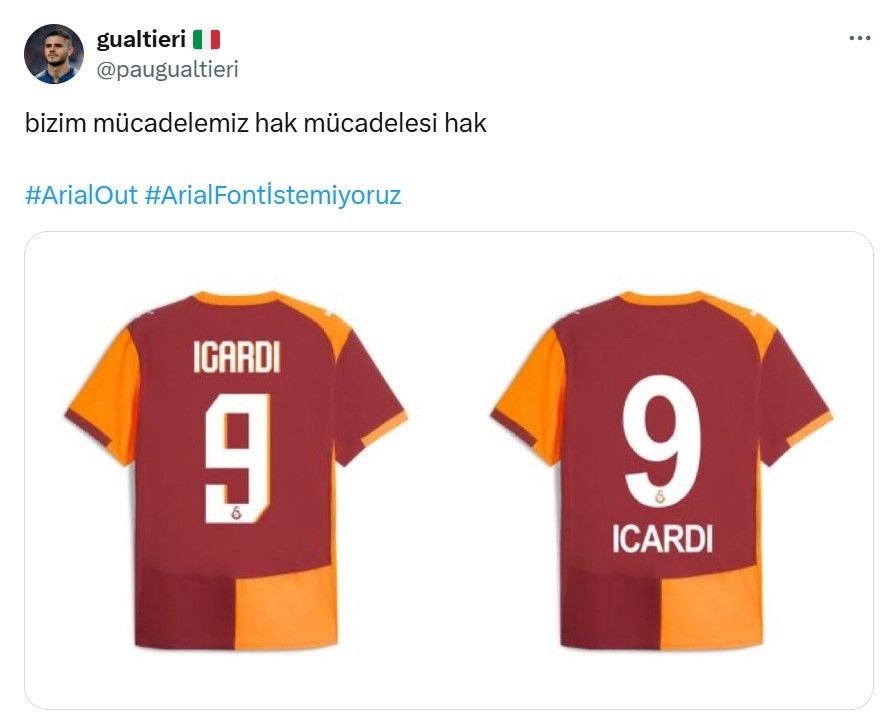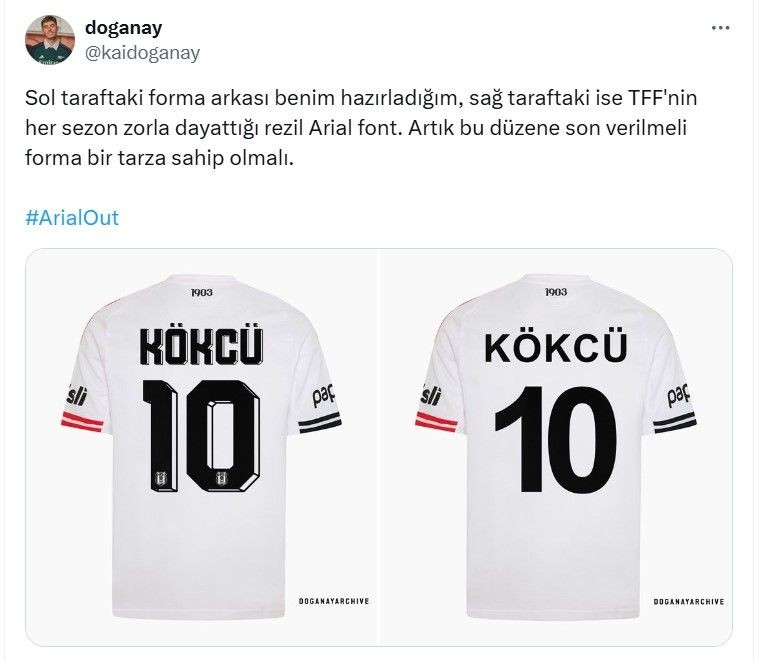
TFF'den 12 yıl sonra tarihi karar! Kural değişiyor
Türkiye Futbol Federasyonu, yaz boyunca taraftarların çağrılarına kulak verdi ve tarihi bir adım atacak.
Galatasaray, Fenerbahçe, Beşiktaş ve Trabzonspor taraftarları başta olmak üzere "#ArialOut #ArialFontİstemiyoruz" etiketleriyle TFF'ye çağrıda bulunmuştu.
Futbolseverler, formalarda Arial font kullanımının zorunlu olmasına tepki göstermiş ve bu konuda çok sayıda paylaşım yapılmıştı.
Umut Eken’in haberine göre TFF Genel Sekreteri Abdullah Ayaz, özellikle sosyal medyadan gelen tepkiler sonrası konuyu gündeme aldı.
TFF yönetimi önümüzdeki hafta yapılacak toplantıda resmi karar alacak. Habere göre; Arial fonta kesin veda ediliyor. İlgili talimat değişecek. Yeni sezonda formalardaki numaralar farklı fontta olacak.